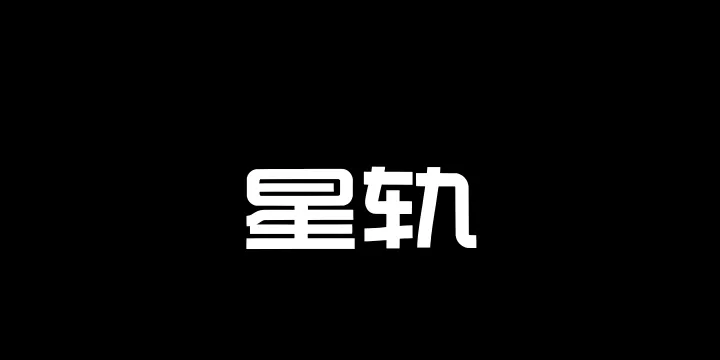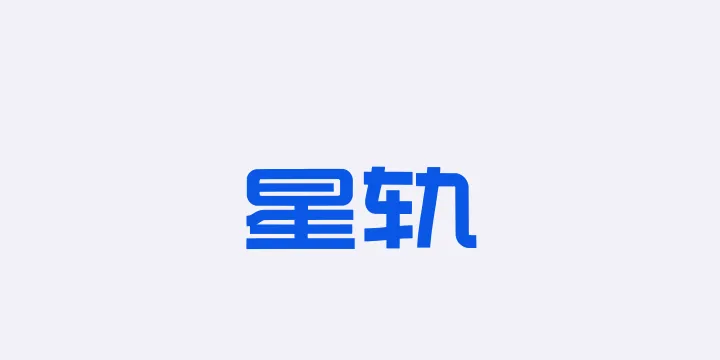
Aa星轨 By Aa字库 商用字体
字体全名: Aa星轨
铸字厂: Aa字库
设计师: Aa字库
字体简介: 这款字体对常规汉字笔画进行高度简化与融合,在等粗黑体的基础上以线条化、圆润化手法重构笔画形态。摒弃了繁复设计细节,笔画没有多余的修饰,线条干净利落。字形扁宽,充满力量感。弧线的加入使字体笔画流转自然婉转,强化了整体感,也在厚重的结构中增添了几分灵动韵律。比起由硬朗线条组成的科技力量感字体,这款字体刚柔对比鲜明,展现出复古未来主义美学。这款字体拥有独特的视觉张力,适合作为标题字体使用,应用于时尚潮流品牌、活动运营海报、电商标题、综艺等场景。